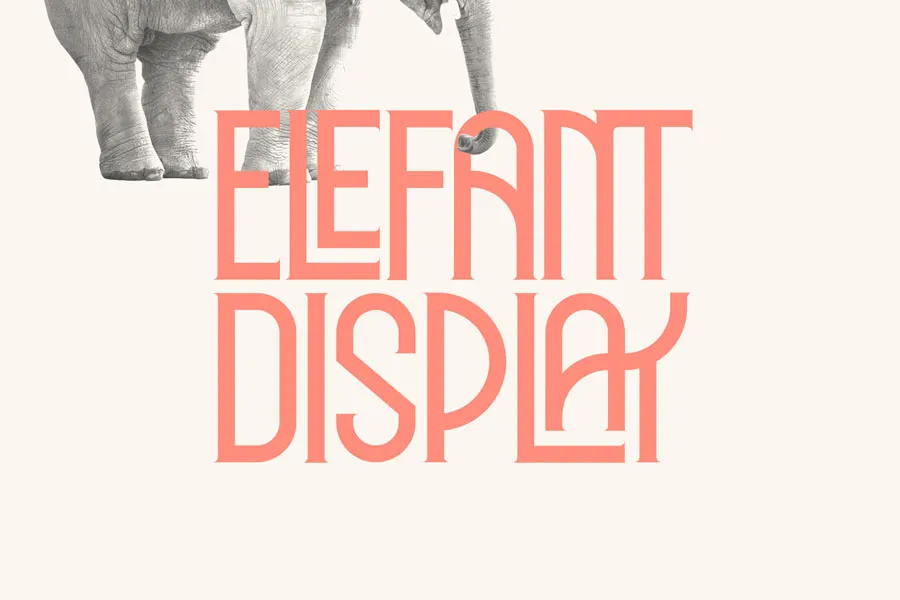
A Elephant Display Font é uma fonte elegante projetada para designers apaixonados por criar visuais impactantes. Perfeita tanto para aplicações digitais quanto impressas, ela oferece a liberdade de expressar sua personalidade criativa num amplo espectro de trabalhos gráficos. Esta fonte idealmente se ajusta a projetos que exigem destaque, como headlines, logotipos e cartazes; também é perfeita para aplicações impressas, como certificados e rótulos. Com suas linhas fortes e elegantes, Elephant Display Font permite que seus designs se destacuem em qualquer formato ou aplicação. Idealmente recomendada para designers com habilidades profissionais, ela oferece a essência de qualidade e destaque necessária para transformar ideias em realidade. Não espere mais: invista na sua identidade visual e experimente a Elephant Display Font agora.